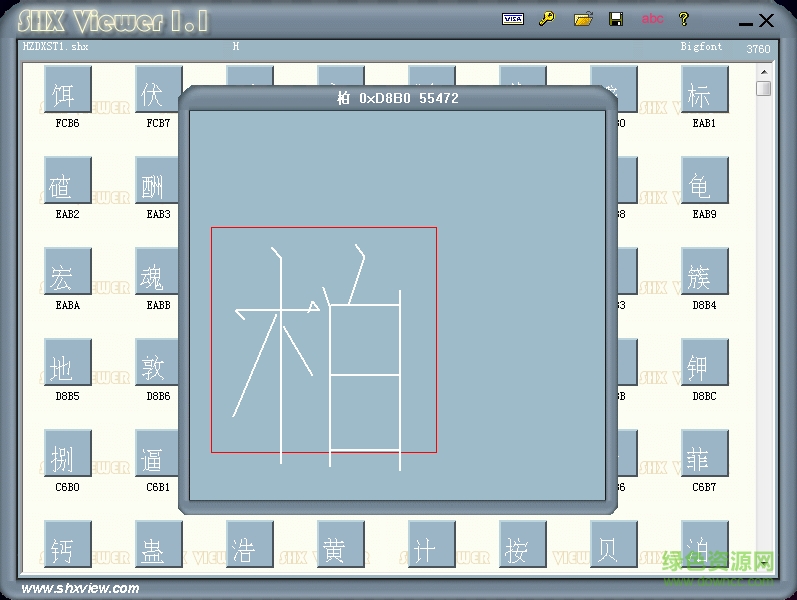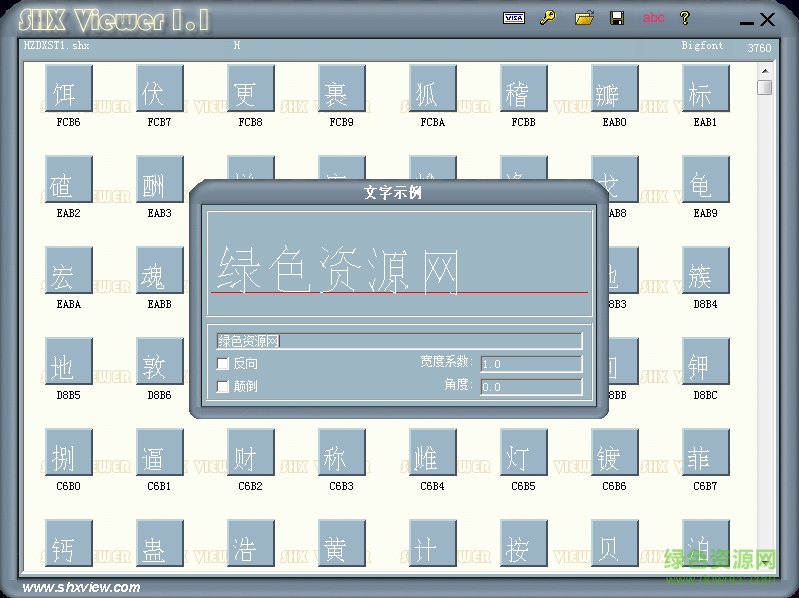
hzdxst.shx是cad中常用的一款中文字體,纖細(xì)娟秀的字體讓你的平面設(shè)計(jì)、工程制作文字更有獨(dú)特魅力,綠色資源網(wǎng)歡迎大家免費(fèi)下載!
作為一款免費(fèi)的Autocad字體庫中的中文字體,支持中英文輸入,有著簡(jiǎn)潔流暢的字形和線條,常被設(shè)計(jì)人士喜愛。